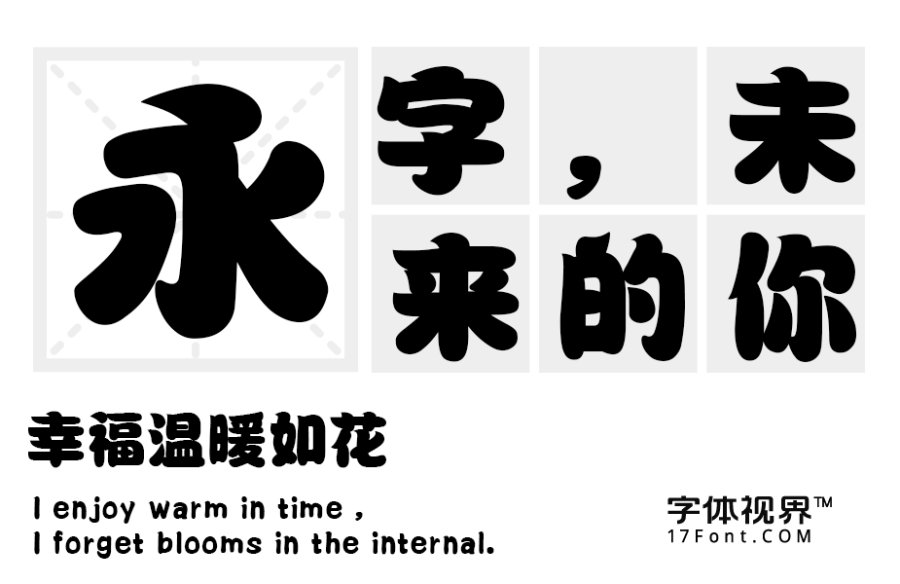
三极丰腴简体发布
字体名称:三极丰腴简体
字体类别: 创意字体
适用场景:标题、LOGO、广告、印刷、屏显、影视
三极丰腴简体简介:三极丰腴简体是一款用短粗笔画特征构成的创意字体,字形丰腴滋润,胖瘦得体,匀称适中。个性天真可爱,富有童趣。适用于杂志、包装和品牌广告宣传设计及标题排版、招牌设计等。
三极丰腴体预览图展示: